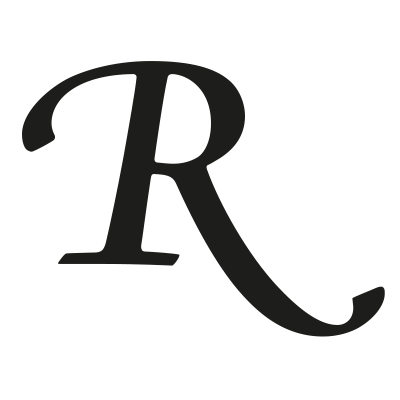
In der Kalligrafie und im Lettering werden die Anfangs- und Endbuchstaben von Wörtern oder Sätzen sowie bestimmte Kleinbuchstaben (meist solche mit mit Ober- und Unterlängen) gern schwungvoller und ausladender ausgestaltet als es bei Satzschriften für Mengentexte üblich oder gar möglich wäre. Auch Satzschriften können jedoch entsprechende Buchstaben als Varianten enthalten, die dann Schwungbuchstaben heißen.
Bei der Anwendung ist darauf zu achten, dass Schwungbuchstaben kontextabhängig gesetzt werden müssen. Schwungbuchstaben sind oft nur für bestimmte Positionen, zum Beispiel den Zeilenanfang oder das Zeilenende, gedacht. OpenType-Schriften können, wenn entsprechend programmiert, die korrekte Aktivierung an der richtigen Stelle auch automatisch erzeugen.